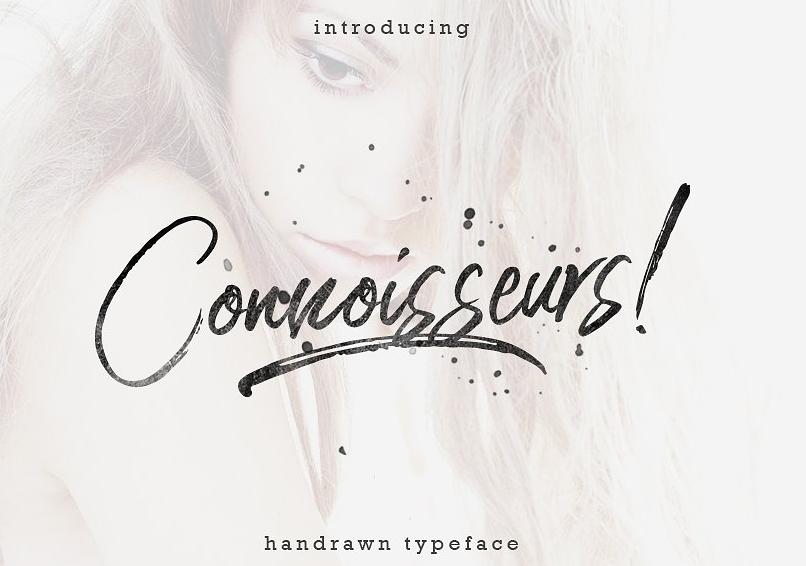
A Connoisseurs Typeface é uma fonte script que cativará qualquer designer ou criador de conteúdo. Seu estilo de escrita delicado mas elegante se assemelha a um traço feito à mão, com um toque de irregularidade que mantém sempre um brilho sofisticado. Introduzida pelo designer 178-MC, esta fonte é perfeitamente adaptada para projetos de marca, design de móveis de casa e embalagens de produtos. Ela também se destaca como uma captação estilosa de texto que enriquece qualquer imagem de fundo. Com um design cuidadosamente elaborado por 178-MC, Connoisseurs é a escolha perfeita para aqueles que buscam uma fonte elegante e única para seus projetos digitais ou impressos.